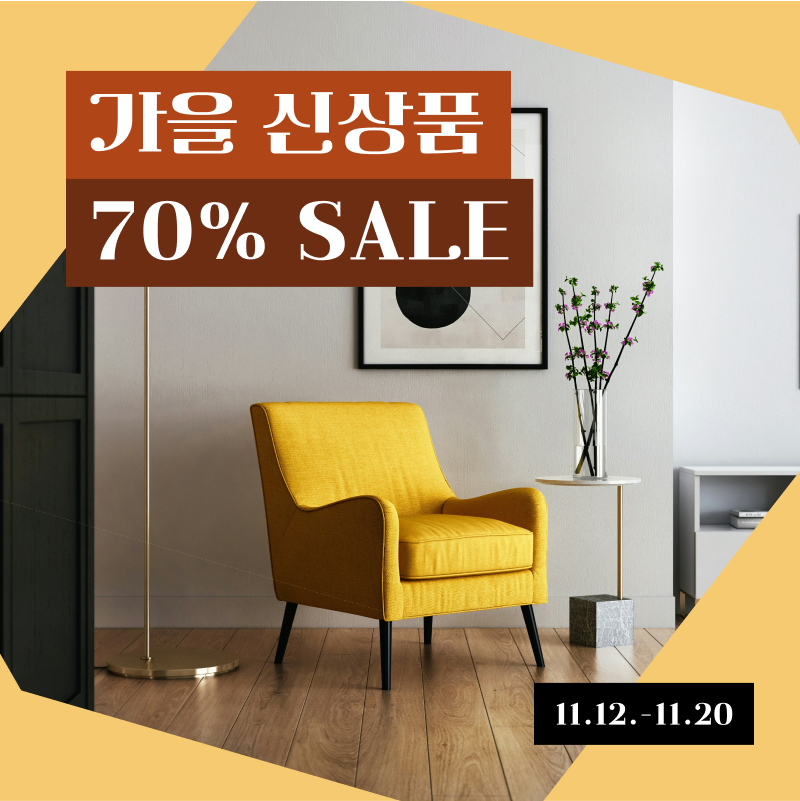
카페24 클래식타입 — Cafe24에서 배포하는 무료 폰트입니다. 옛 교과서 활자에서 가져온 고전풍 헤드라인 서체
카페24가 2022년 5월에 공개한 스무 번째 무료 서체입니다. 카페24 서체 가운데 회사가 조형을 직접 설명한 드문 경우라, 그 문장을 그대로 옮깁니다.
1910년대 미국 초등학교 교과서에 쓰고자 개발된 고전 서체 센추리 스쿨북의 부드러운 곡선과 명료한 직선 디자인을 현대적으로 재해석한 폰트라는 것입니다. 글자 획 끝에 있는 세리프를 적용해 이목을 집중시켜야 하는 상세페이지와 프로모션, 배너 같은 콘텐츠의 헤드라인과 브랜드 로고에 활용하기 적합하다고 덧붙입니다.
파일에서 재어 보면 낱자가 가로로 퍼져 있고 자면을 넉넉히 채워, 짧은 제목을 크게 세울 때 존재감이 있습니다. 굵기는 하나뿐이고 회사 스스로 헤드라인용으로 규정했으니 긴 본문에는 맞지 않습니다. 현대 한글 11,172자를 모두 담았습니다.